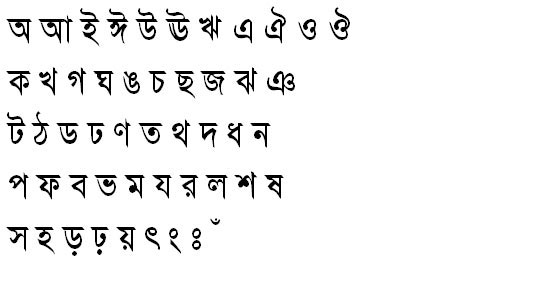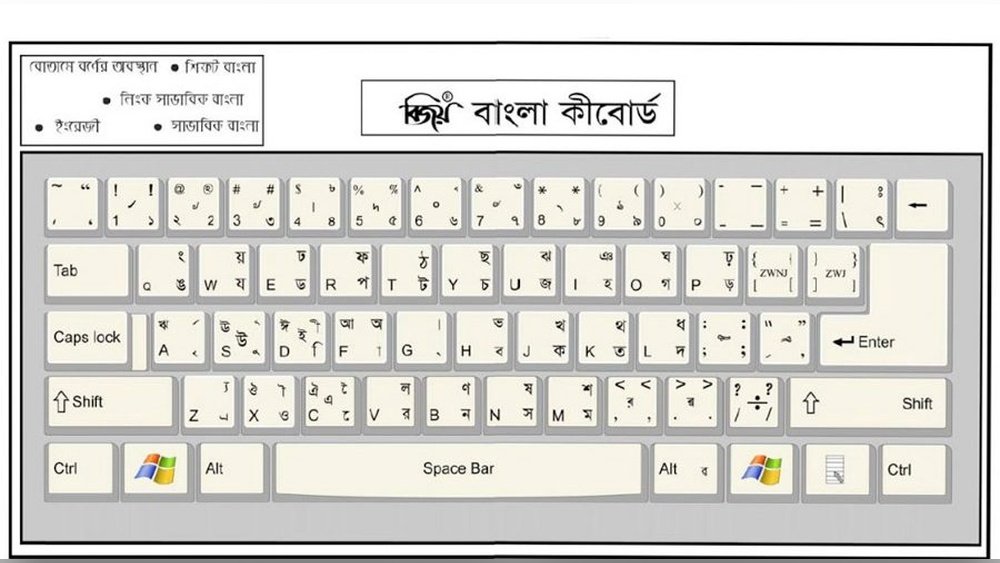
আপনি কি বাংলা টাইপিং এর জন্য একটা সহজ, দ্রুত এবং জনপ্রিয় ফন্ট খুঁজছেন? তাহলে “Bijoy Bangla Font Free Download” আপনার জন্য একদম সঠিক অপশন। এই ফন্টটি বাংলা লেখার কাজকে করে তোলে অনেক মসৃণ ও সুন্দর। আপনি যদি অফিসের কাজ, স্কুল প্রজেক্ট, ব্লগ অথবা যেকোনো ডিজিটাল মিডিয়াতে বাংলা লেখেন, তাহলে বিজয় বাংলা ফন্ট আপনার কাজের গুণগত মান বাড়িয়ে দেবে। এই আর্টিকেলে আমরা আপনাকে দেখাবো কিভাবে সহজেই বিনামূল্যে বিজয় বাংলা ফন্ট ডাউনলোড করবেন এবং সেটআপ করবেন, যাতে আপনি দ্রুত আপনার কাজ শুরু করতে পারেন। তাই পুরো পোস্টটি মনোযোগ দিয়ে পড়ুন, আপনার টাইপিং অভিজ্ঞতা বদলে যাবে!
বিজয় বাংলা ফন্ট পরিচিতি
বিজয় বাংলা ফন্ট বাংলা ভাষাভাষীদের জন্য অত্যন্ত পরিচিত ও জনপ্রিয় একটি ফন্ট। এটি সহজেই বাংলায় লেখালেখির কাজকে সুন্দর ও পেশাদারী করে তোলে। বিজয় বাংলা ফন্ট ব্যবহার করলে লেখার গুণগত মান বৃদ্ধি পায় এবং চোখে পড়ার মতো আকর্ষণ তৈরি হয়।
বিজয় বাংলা ফন্ট মূলত বাংলা ভাষার বিশেষ চাহিদা মেটাতে ডিজাইন করা হয়েছে। এটি বিভিন্ন ধরণের ডকুমেন্ট, ব্লগ, ওয়েবসাইট এবং গ্রাফিক ডিজাইনে ব্যবহার করা যায়। এই ফন্টটি বিনামূল্যে ডাউনলোড করা যায়, যা ব্যবহারকারীদের জন্য অনেক সুবিধাজনক।
বিজয়ের ইতিহাস
বিজয় বাংলা ফন্টের সূচনা হয়েছিল বাংলা টাইপিং এবং ডিজিটাল লেখার সহজতা বৃদ্ধির জন্য। এটি প্রথম তৈরি হয়েছিল ১৯৮০-এর দশকে। তখন বাংলা কম্পিউটিং খুব সীমিত ছিল।
বিজয় ফন্টের মাধ্যমে বাংলা লেখার কাজ অনেক সহজ হয়। এটি কম্পিউটার ও বিভিন্ন সফটওয়্যারে সহজেই ব্যবহার করা যায়। বিজয় ফন্টের জনপ্রিয়তা দ্রুত বৃদ্ধি পায়।
বিজয় ফন্টের বৈশিষ্ট্য
বিজয় বাংলা ফন্টের একাধিক বিশেষ বৈশিষ্ট্য রয়েছে। এটি স্পষ্ট ও পাঠযোগ্য। ছোট আকারেও চোখে পড়ে।
ফন্টটি বিভিন্ন ডিভাইসে সঠিকভাবে প্রদর্শিত হয়। এটি ইউনিকোড নয়, তাই কিছু সফটওয়্যারে আলাদা ব্যবহার করতে হয়।
বিজয় ফন্টের সাহায্যে দ্রুত বাংলা টাইপ করা যায়। এটি বাংলা লেখার কাজকে আরও সহজ ও মসৃণ করে তোলে।
বিজয় ফন্ট ব্যবহার করার সুবিধা
বিজয় ফন্ট ব্যবহার করলে টাইপিং এবং লেখালেখির কাজ অনেক সহজ হয়। এই ফন্টটি বাংলা ভাষায় কাজ করার জন্য বিশেষভাবে ডিজাইন করা হয়েছে। ফলে লেখার গতি বাড়ে এবং কাজের মান উন্নত হয়। বিজয় ফন্টের সাহায্যে লেখকরা দ্রুত ও সুন্দরভাবে বাংলা লিখতে পারেন।
বিজয় ফন্টের আরেকটি বড় সুবিধা হলো এটি বিভিন্ন সফটওয়্যারে ভালো সমর্থন দেয়। তাই আপনি যেকোনো জনপ্রিয় সফটওয়্যার বা প্ল্যাটফর্মে সহজেই এই ফন্ট ব্যবহার করতে পারবেন। এতে কাজের ধারাবাহিকতা বজায় থাকে এবং সময় বাঁচে।
দ্রুত টাইপিং সুবিধা
বিজয় ফন্টে বাংলা টাইপিং অনেক দ্রুত হয়। কীবোর্ডের সঙ্গে ফন্টের সঠিক মিল থাকায় টাইপিং সহজ হয়। টাইপ করার সময় বানানে ভুল কম হয়। যারা বাংলা লেখা বেশি করেন তাদের জন্য এটি সময় বাঁচানোর এক ভালো উপায়।
বিভিন্ন সফটওয়্যারে সমর্থন
বিজয় ফন্ট প্রায় সব জনপ্রিয় সফটওয়্যার সমর্থন করে। যেমন: মাইক্রোসফট ওয়ার্ড, এক্সেল, পাওয়ারপয়েন্ট, এবং বিভিন্ন গ্রাফিক ডিজাইন সফটওয়্যার। এতে কাজের মধ্যে কোনো অসুবিধা হয় না। ফন্টটি উইন্ডোজ ও ম্যাক উভয় প্ল্যাটফর্মেই ব্যবহারযোগ্য।
বিজয় ফন্টের বিকল্প এবং অন্যান্য জনপ্রিয় বাংলা ফন্ট
বিজয় ফন্ট বাংলা লেখার জন্য সবচেয়ে জনপ্রিয় ফন্টগুলোর মধ্যে একটি। অনেক সময় বিভিন্ন কাজে বিজয় ফন্টের বিকল্প ফন্টের দরকার পড়ে। এছাড়া, বাংলা ভাষায় কাজ করার জন্য অনেক জনপ্রিয় ফন্ট রয়েছে যা ইউনিকোড এবং নন-ইউনিকোড হিসেবে বিভক্ত। এই ফন্টগুলো ব্যবহার করে বাংলা লেখাকে আরও সহজ এবং সুন্দর করা যায়।
বিভিন্ন প্রকারের ফন্ট ব্যবহার করে বাংলা লেখার গুণগত মান বৃদ্ধি পায়। তাই বিজয় ফন্টের বিকল্প এবং অন্যান্য জনপ্রিয় বাংলা ফন্ট সম্পর্কে জানা গুরুত্বপূর্ণ।
নন-ইউনিকোড ফন্টের তালিকা
নন-ইউনিকোড ফন্টগুলো প্রায়শই পুরানো সফটওয়্যার এবং কম্পিউটারে ব্যবহৃত হয়। এই ফন্টগুলোতে বাংলা অক্ষর গুলো নির্দিষ্ট কোডিং সিস্টেম ছাড়া কাজ করে।
বিজয় বাংলা ফন্ট ব্যবহার করলে বাংলা লেখার মান উন্নত হয়। এটি দ্রুত টাইপিং এবং সহজ সম্পাদনার সুযোগ দেয়। এছাড়া এটি বিভিন্ন প্রিন্ট ও ডিজিটাল মিডিয়ায় সুন্দর দেখায়।
Conclusion
বিজয় বাংলা ফন্ট ফ্রি ডাউনলোড করে আপনার বাংলা লেখাকে আরও সুন্দর করুন। এই ফন্টটি ব্যবহার সহজ এবং দ্রুত ইনস্টল হয়। যেকোনো কম্পিউটার বা মোবাইলে ব্যবহার করতে পারেন। বাংলা লেখার মান বাড়াতে এটি উপযুক্ত একটি ফন্ট। তাই আজই ডাউনলোড করুন এবং আপনার কাজকে আরও প্রফেশনাল করুন। নির্ভয়ে ব্যবহার করুন, কারণ এটি সম্পূর্ণ ফ্রি এবং নিরাপদ। বিজয় বাংলা ফন্টের মাধ্যমে বাংলা ভাষার প্রকাশ আরও সহজ ও সাবলীল হবে।